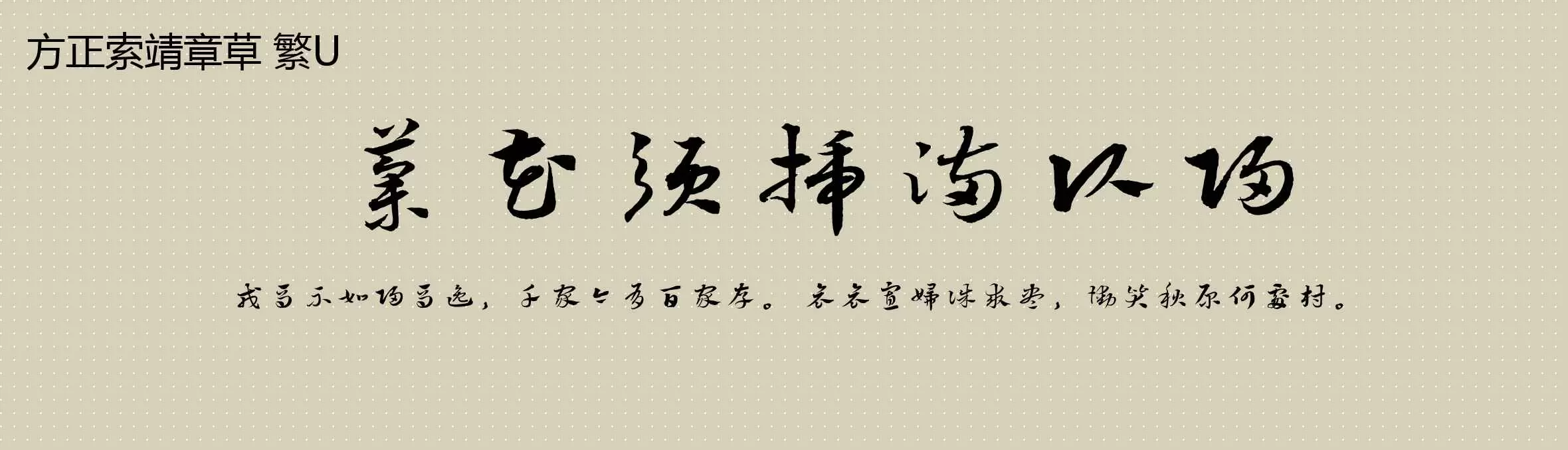
方正索靖章草以索靖的章草名作《月仪帖》为临创开发依据,字形内涵朴厚,字势风神凛然、雄勇劲健,结体知趣自然、妙有余姿。适合应用于标题、海报、书籍、广告、影视、招牌、游戏等领域。索靖(239~303年),字幼安。西晋将领、著名书法家,敦煌五龙之一。索靖的章草自成一家,被张怀瓘评道“有若山形中裂,水势悬流,云岭孤松,冰河危石,其坚劲则古今不逮。”著有《草书状》等。